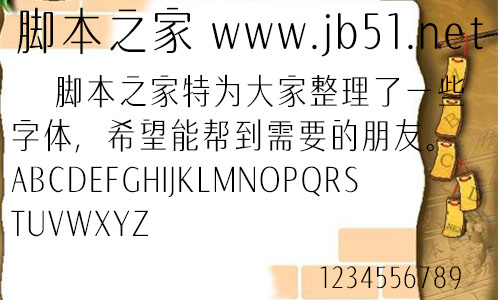
火山字型修竹圆/方是火山字型推出的火山字型修竹字体的两种字形,方字形笔触较圆字形笔触略细,字形端正,适合应用于艺术设计、各类广告和产品包装设计等领域。
火山字型,由一位从业多年的平面设计师创建,每套字体的风格设定皆来自日常设计需求中,从2016年开始成体系的制作中文字库,在2020年6月1日正式公开发行三套原创中文字型——眉月、悍石、修竹。